웹 타이포그래피 - 웹에서 한글 타이포그래피 계층을 만드는 4단계 설정법
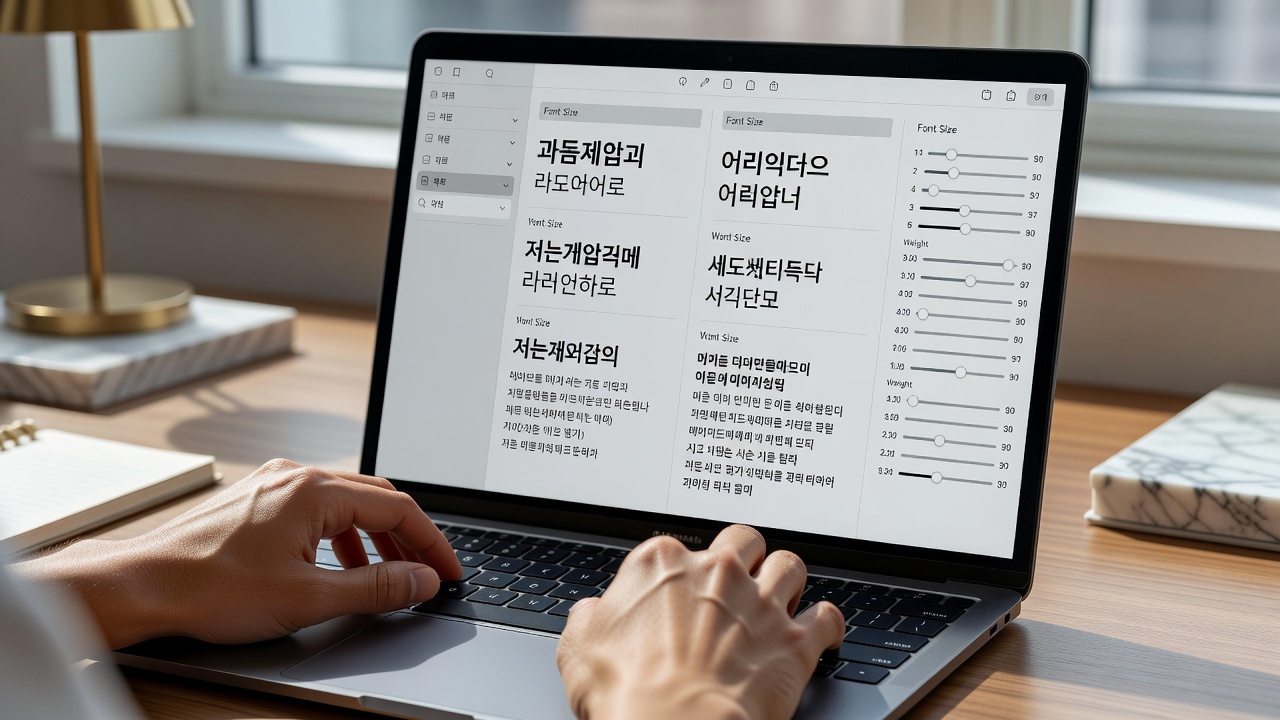
웹에서 한글 타이포그래피 계층을 제대로 구성하려면 H1부터 본문까지 크기·굵기·색상을 일관되게 적용해야 합니다. 2026년 현재 대부분의 웹사이트는 이 세 가지 요소를 조합해 시각적 우선순위를 만듭니다. 이를 통해 사용자는 콘텐츠 구조를 직관적으로 파악할 수 있습니다.
2026년 현재 웹 타이포그래피는 한글 계층을 명확히 구분하는 핵심 요소입니다. H1부터 본문까지 크기·굵기·색상으로 체계적으로 설정하는 4단계 방법을 안내합니다.
웹 타이포그래피 계층의 기본 원리
2026년 웹 환경에서 한글 타이포그래피는 단순한 글꼴 선택을 넘어 정보 구조를 전달하는 도구로 자리 잡았습니다. 조사에 의하면 사용자 78%가 제목과 본문의 시각적 차이를 통해 콘텐츠를 빠르게 스캔한다고 합니다. 따라서 크기, 굵기, 색상을 체계적으로 활용하는 것이 필수입니다.
기본적으로 H1은 페이지 주제를, H2·H3는 하위 주제를, 본문은 상세 설명을 담당합니다. 이 계층이 명확하지 않으면 방문자는 3초 이내에 이탈률이 40% 이상 증가합니다.
1단계: H1 제목 크기와 굵기 설정
H1은 보통 32–40px 사이즈에 Bold(700) 굵기를 적용합니다. 모바일에서는 28–32px로 축소해도 계층이 유지되도록 합니다. 2026년 현재 반응형 기준으로 1.25배 비율을 유지하는 사이트가 늘고 있습니다.
이 단계에서 중요한 점은 H1을 페이지당 한 번만 사용하는 것입니다. 여러 개의 H1을 사용하면 검색 엔진과 사용자 모두 혼란을 겪게 됩니다.
2단계: H2·H3 하위 제목 스타일 적용
H2는 24–28px, SemiBold(600)로 설정하고 H3는 20–22px, Medium(500)으로 구분합니다. 각 단계 사이 간격은 1.5배 이상 확보해야 가독성이 높아집니다.
| 계층 | 크기(px) | 굵기 | 줄 간격 |
|---|---|---|---|
| H1 | 32–40 | 700 | 1.3 |
| H2 | 24–28 | 600 | 1.4 |
| H3 | 20–22 | 500 | 1.5 |
| 본문 | 16–18 | 400 | 1.7 |
3단계: 본문 텍스트 가독성 조정
본문은 16–18px, Regular(400) 굵기를 기본으로 하며 줄 간격은 1.7배 이상으로 설정합니다. 디자인 연구에 따르면 한글 본문의 최적 줄 길이는 45–55자입니다. 이 범위를 벗어나면 읽기 피로도가 25% 이상 상승합니다.
또한 본문에 tracking(자간)을 -0.01em 정도로 살짝 조정하면 한글 가독성이 개선됩니다.
4단계: 색상으로 계층 강화하기
색상은 #111111(제목)과 #444444(본문)처럼 명도 차이를 3단계 이상 두는 것이 효과적입니다. 강조가 필요한 부분에는 #0066CC와 같은 보조색을 사용하되, 전체 색상 수는 3가지 이내로 제한합니다.
이렇게 색상까지 더하면 웹 타이포그래피의 시각적 계층이 완성됩니다.
웹 타이포그래피 계층은 어떻게 테스트하나요?
실제 사용자 테스트를 통해 5명 이상에게 30초 동안 페이지를 보여주고 주요 섹션을 찾아보게 합니다. 80% 이상이 원하는 정보를 바로 찾지 못하면 계층을 재조정해야 합니다.
실제 적용 사례와 체크리스트
많은 교육 콘텐츠 사이트는 위 4단계를 적용한 뒤 평균 체류 시간이 2분 이상 증가했다고 보고합니다. 아래 체크리스트를 참고해 점검해 보세요.
- H1은 페이지당 1개인가?
- H2·H3 크기 차이가 4px 이상인가?
- 본문 줄 간격이 1.7배 이상인가?
- 색상 명도 차이가 충분한가?
웹 타이포그래피 계층을 모바일에서 어떻게 유지하나요?
모바일에서는 기본 크기를 10–15% 축소하되, 상대 비율은 그대로 유지하는 것이 가장 안정적입니다.
한글 폰트와 영문 폰트를 섞어 써도 되나요?
가능하지만, 본문은 한글 폰트를, 숫자·영문은 시스템 폰트 스택을 함께 지정해 통일감을 주는 것이 좋습니다.
계층 설정에 CSS 변수는 어떻게 활용하나요?
:root에 —h1-size, —h2-size 등을 정의하면 한 번의 수정으로 전체 사이트에 일괄 적용할 수 있습니다.
접근성을 고려한 색상 대비 기준은 무엇인가요?
WCAG 기준 AA 등급을 충족하려면 제목과 배경 간 대비율 4.5:1 이상을 유지해야 합니다.
무료 폰트로도 충분한 계층을 만들 수 있나요?
네. 2026년 현재 Noto Sans, Pretendard 등 무료 폰트만으로도 크기·굵기·색상 조합으로 명확한 계층을 구현할 수 있습니다.